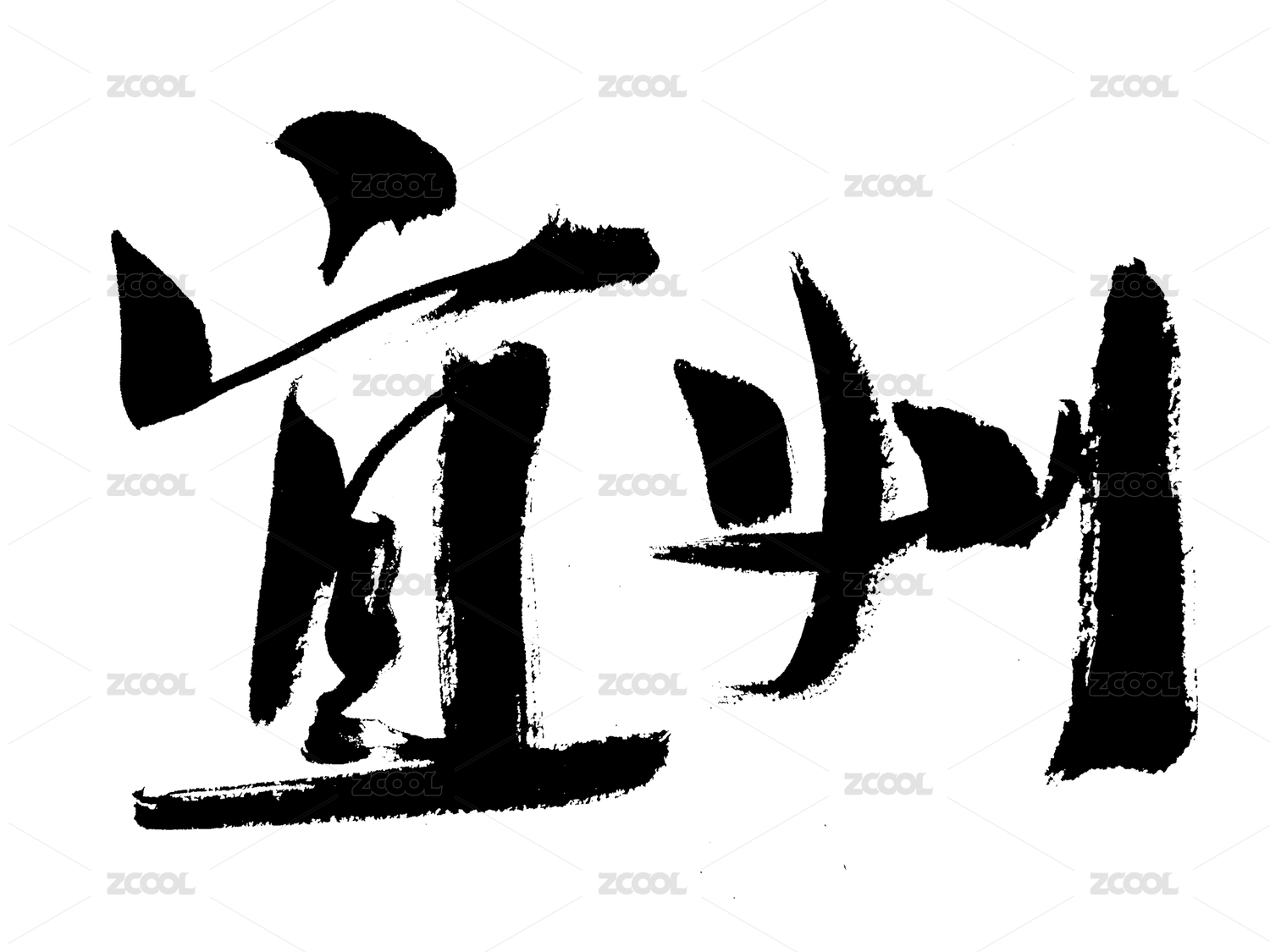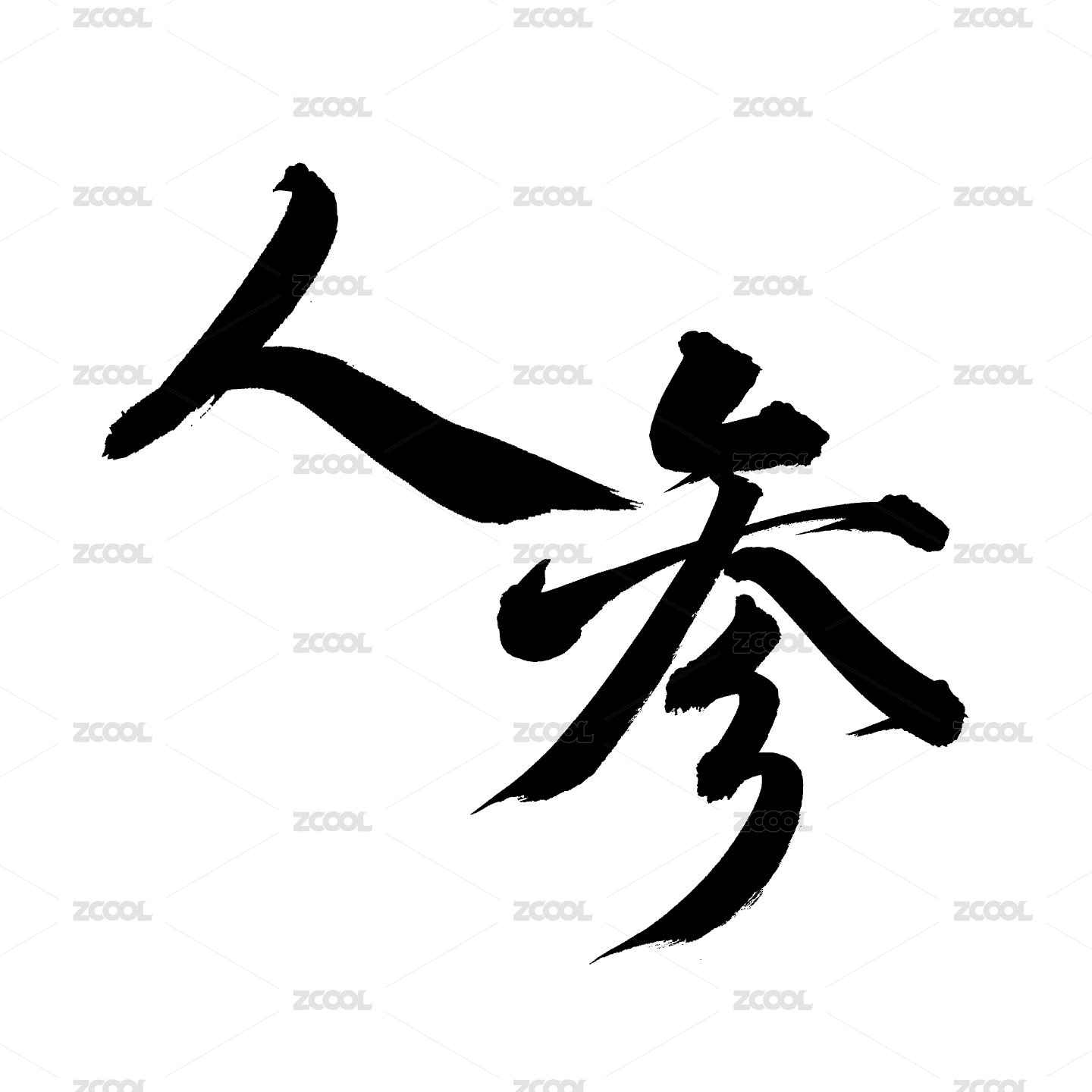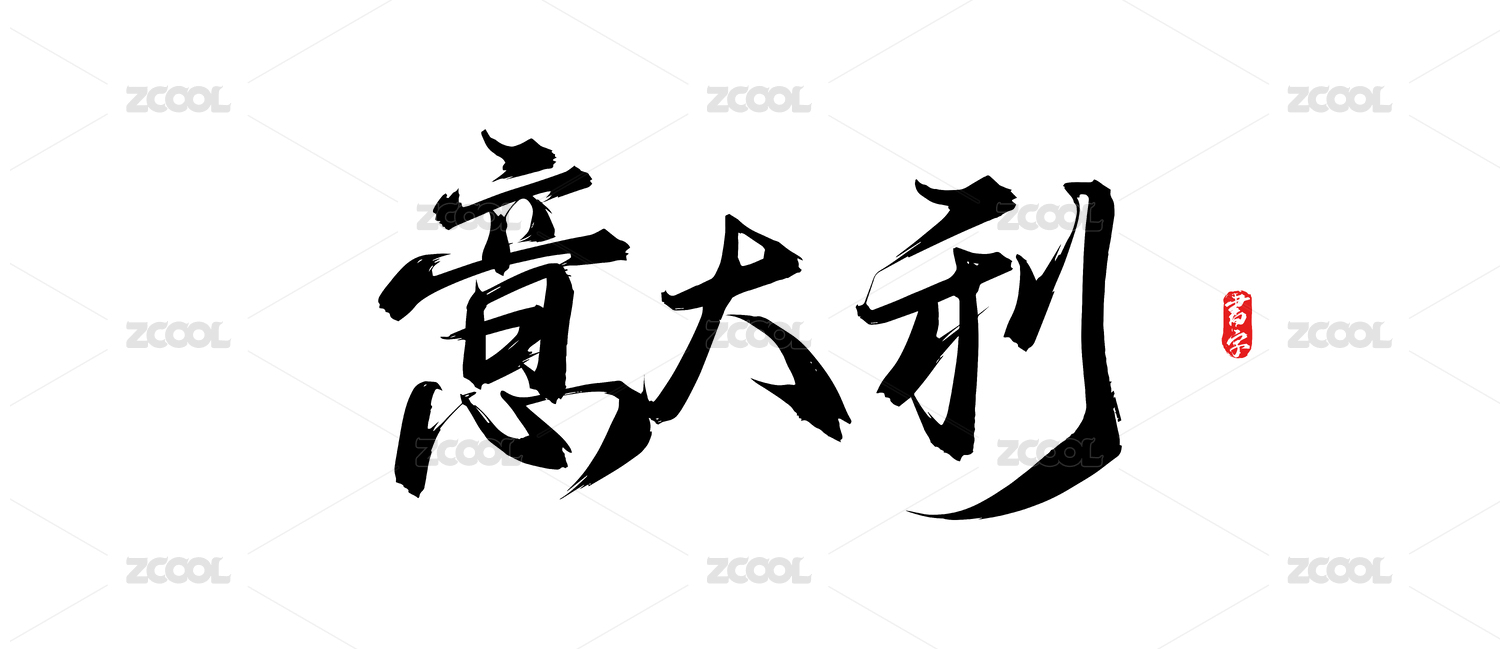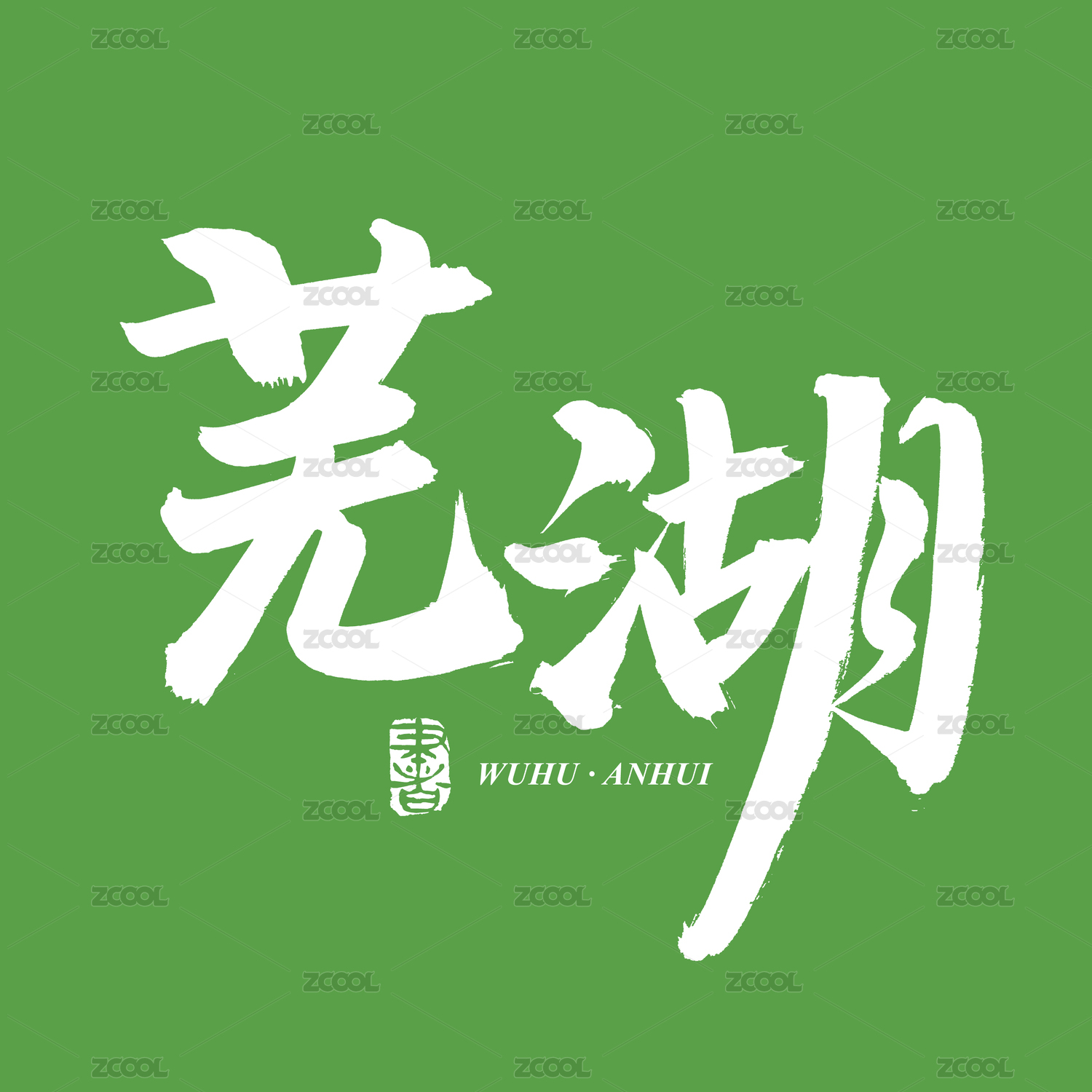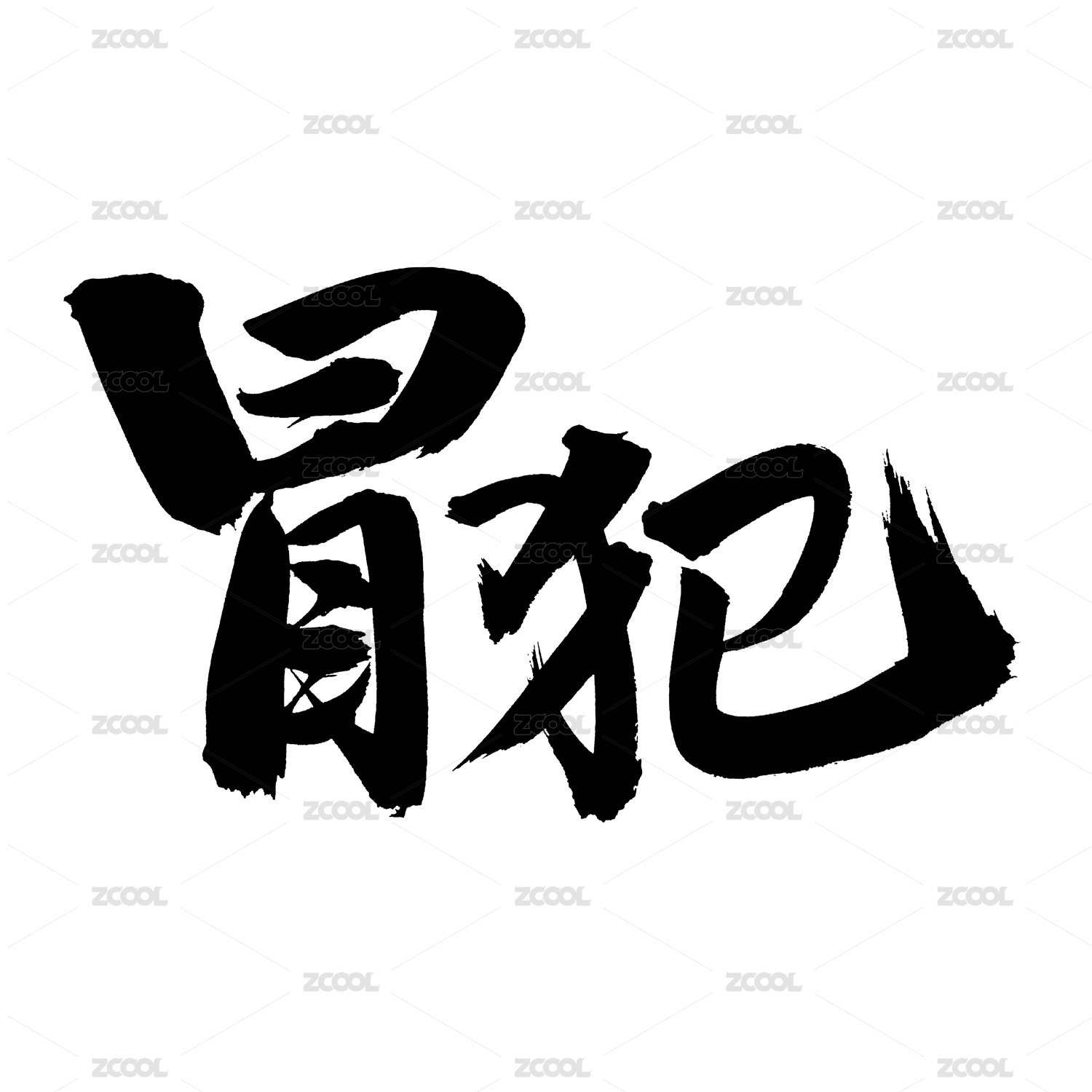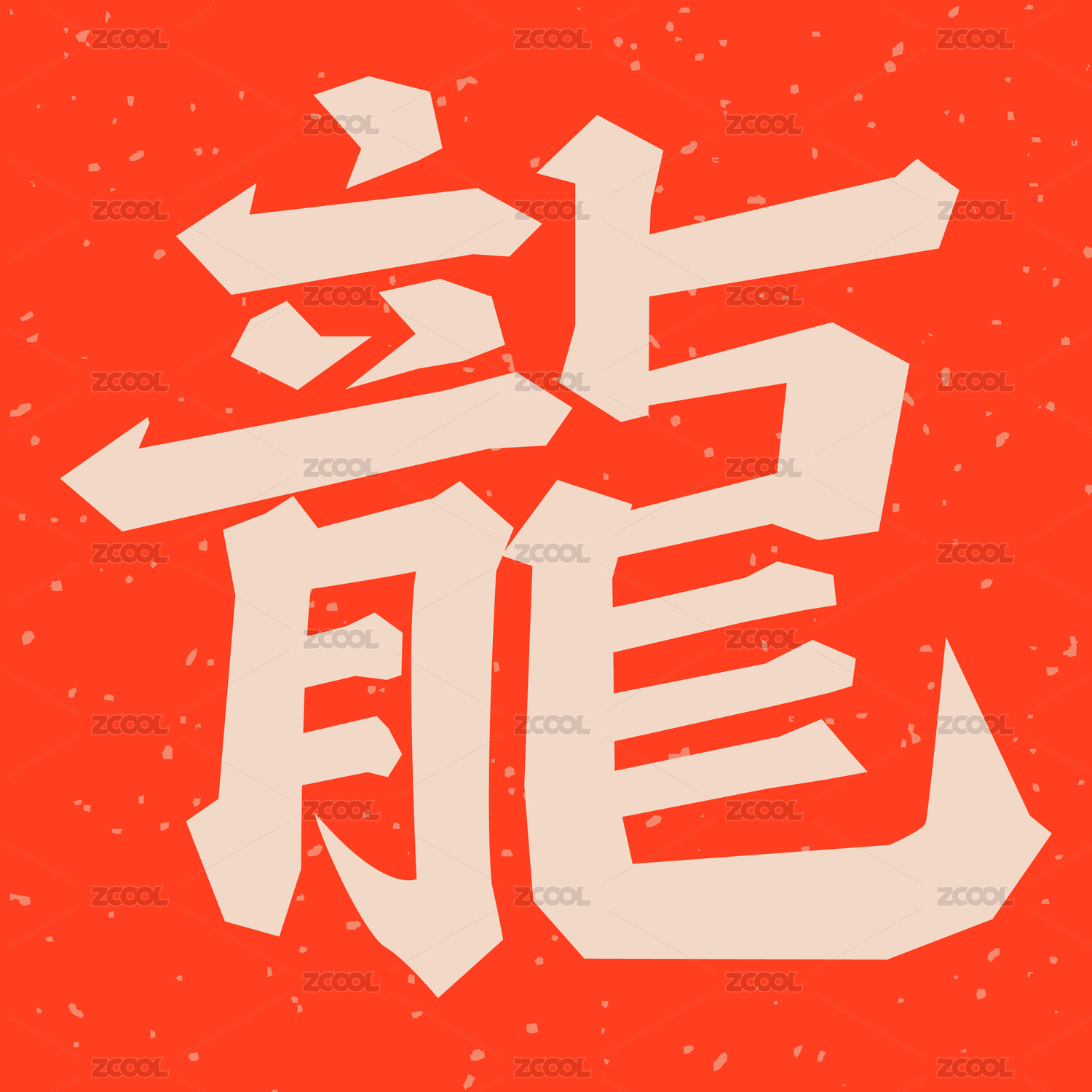
意墨─刘浪四月草书作品集
劉浪
墨怀相生,元心未变
墨韵之怀在于憶之间,年少时吾好笔墨之意,随之墙面乱涂为童年之趣也,可为心之所向。意在笔先,好古书情游伴年少之时。并印之为我何时之用也。可谓元心之初,笔墨生情寄于时光之间。元心之意,起为初心之真。真者何乐而不为,由心所畅,游目骋怀于笔墨之间。墨韵相生,意念相境,得之为我失,变之为我知。何时不意笔墨之书,墨怀相生墨在于心,怀在于勤,寄托于笔墨知己。元心末变长叙,感怀助我学书之师者也开之引行书法之间,笔情志通。吾能而立者矣。知者可以忆昔日,山水之间。通逸雅观墨韵,可悟左右通达,其心尚技于草书之情,墨攻五体为终生,从心通逸,墨志传统,逸雅经典,墨曲悠然自得,会意其乐。五体书法由见者,吾之篆籀笔法之意,心之所向求学之路为逸庐学书,通我思书之想,可谓善其笔之表达也。通达进其观也,皆为五体兼养于书,浩然正气目由相生,即为我元心之至,墨怀─忆在远方者之境也。